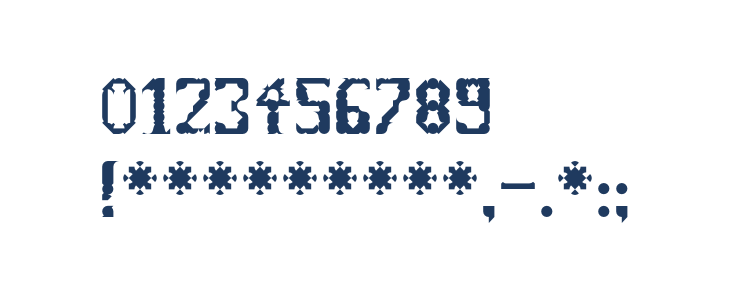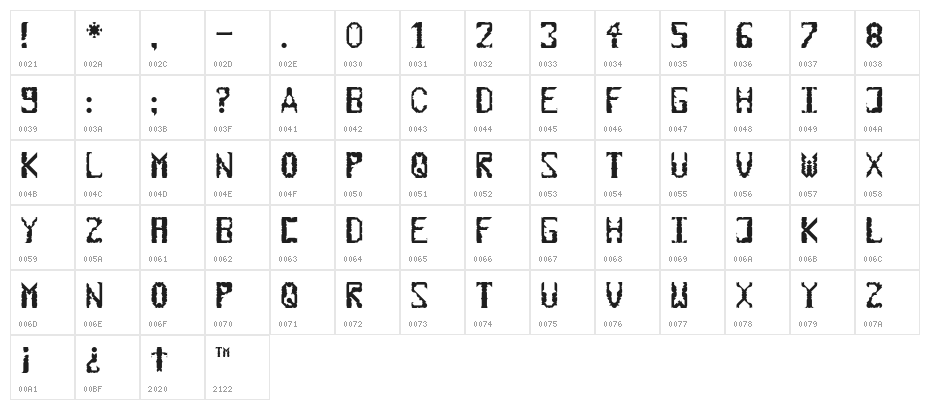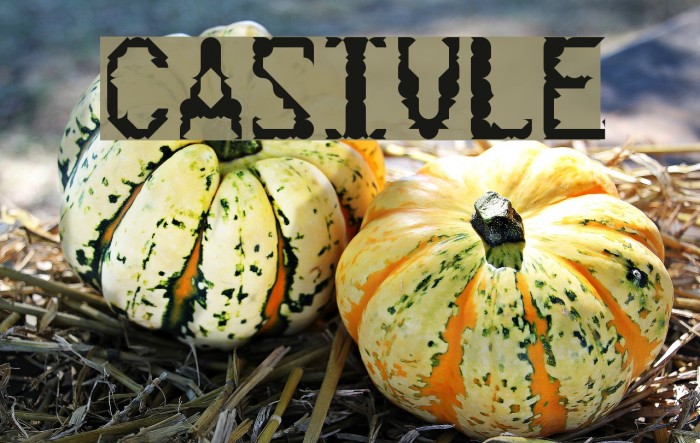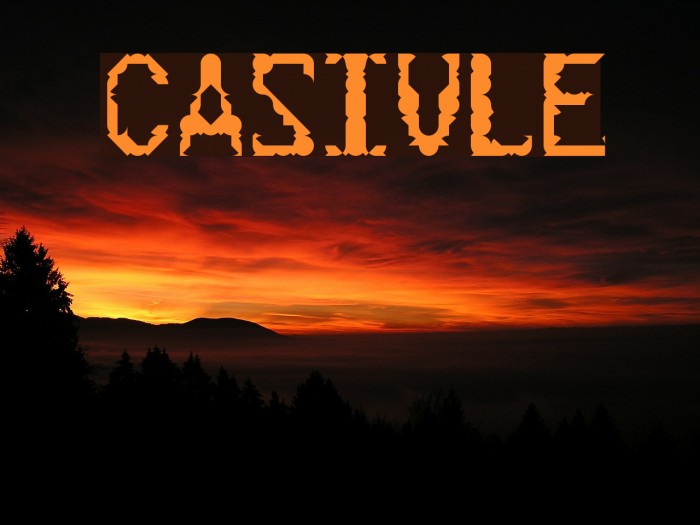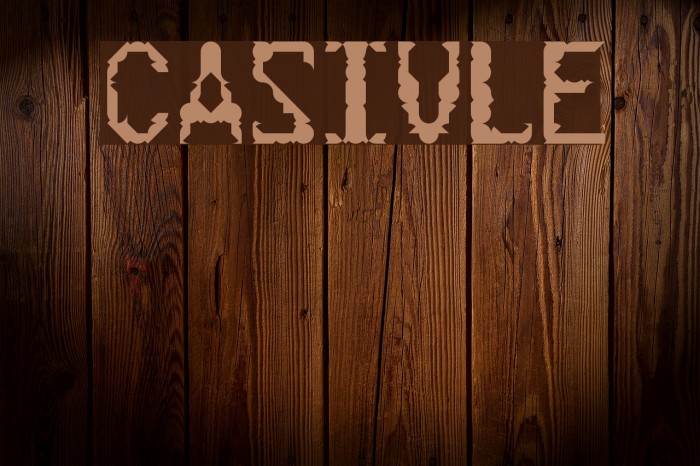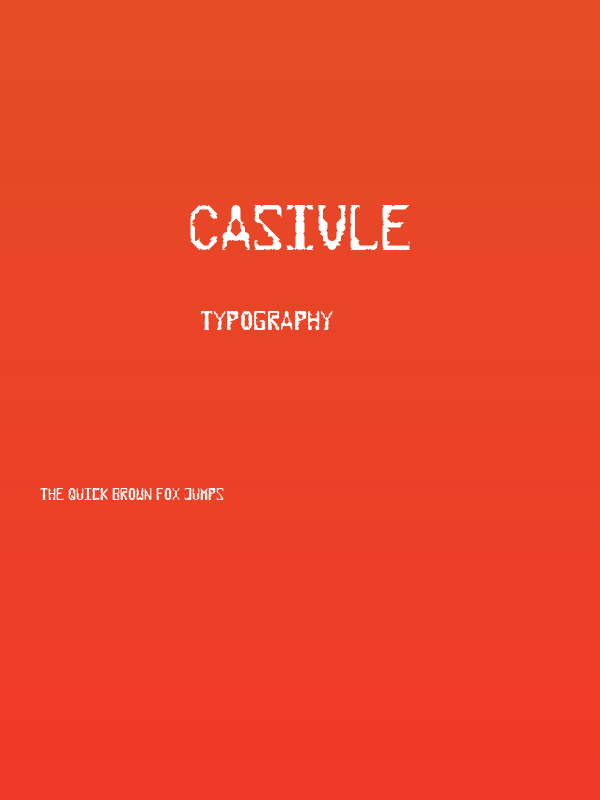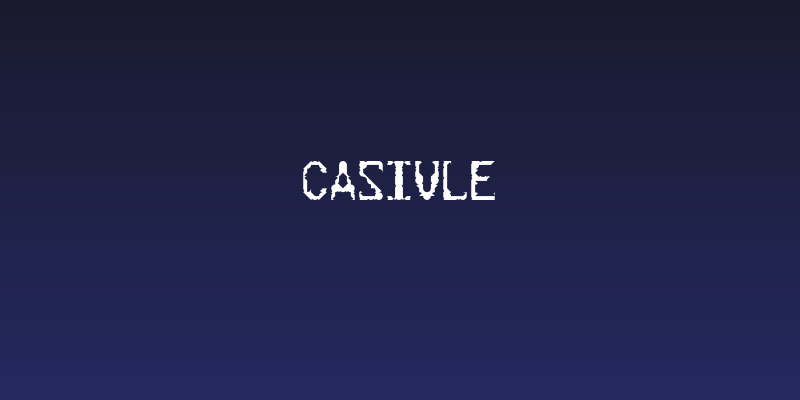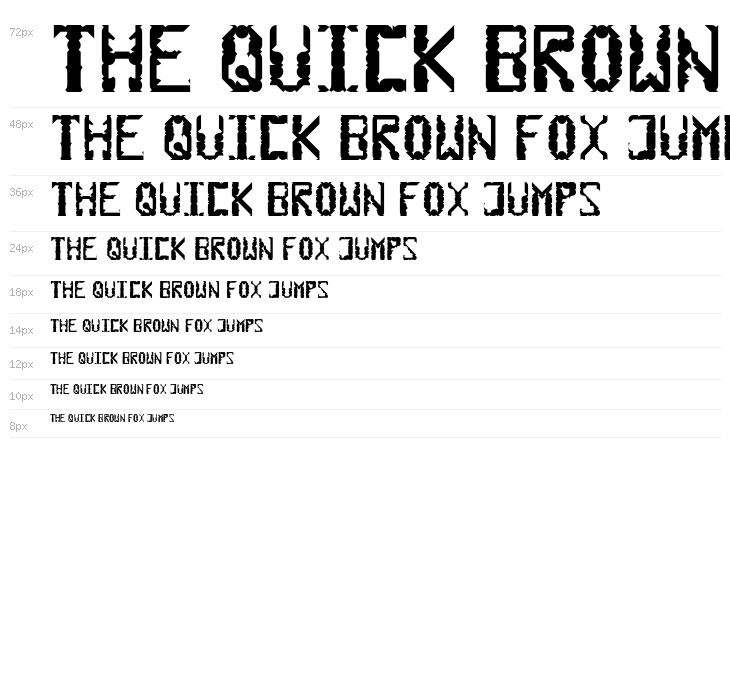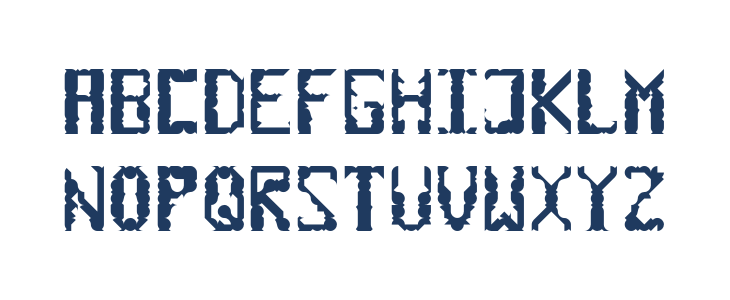
CASivle Font
✎ Distorted Eroded
| Categorías | Distorted Eroded |
| Estilo general | Industrial, Grunge |
| Proyectos propuestos | Ideal for projects that require a gritty, industrial feel such as band posters, urban-themed designs, or video game graphics. |